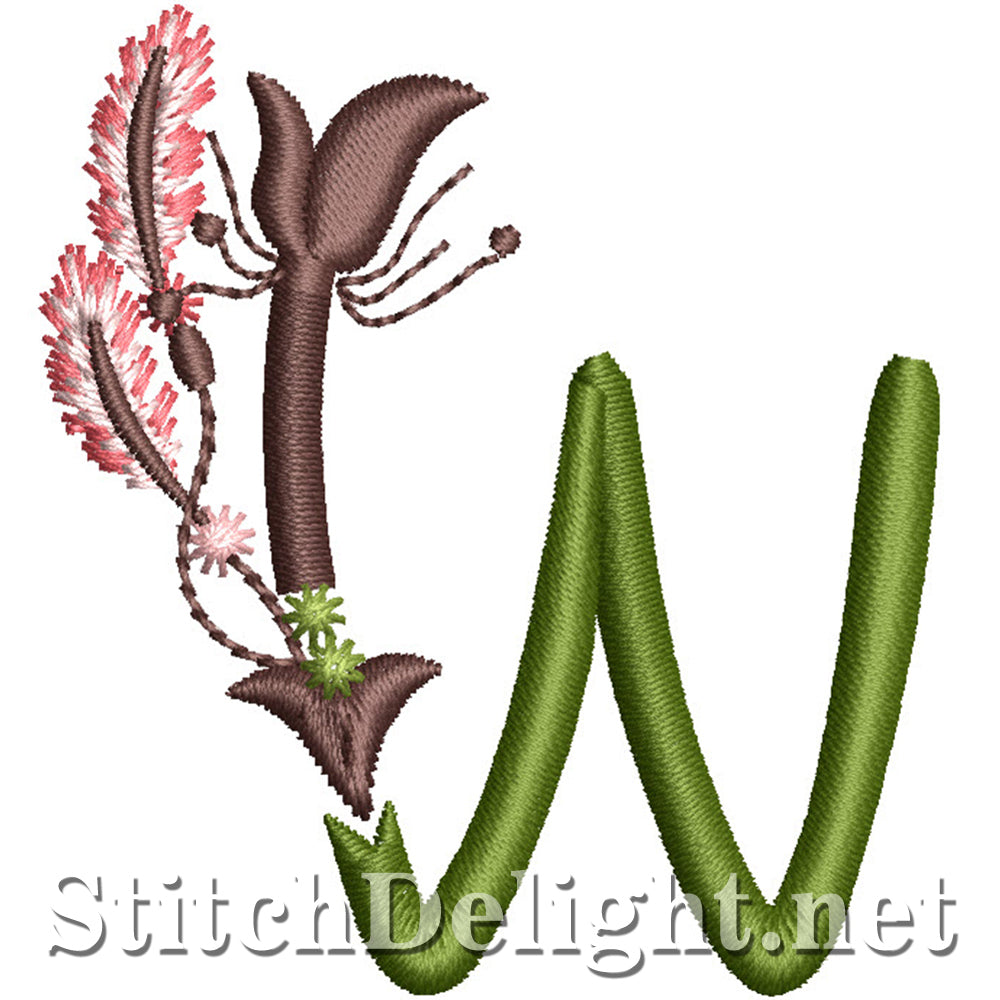
SDS1759 Boho Baby Police W
Cette adorable lettre unique est conçue pour le cerceau 4x4 et est parfaite pour une utilisation sur des vêtements et du linge, elle se brodera également de manière époustouflante sur des sacs en tissu !